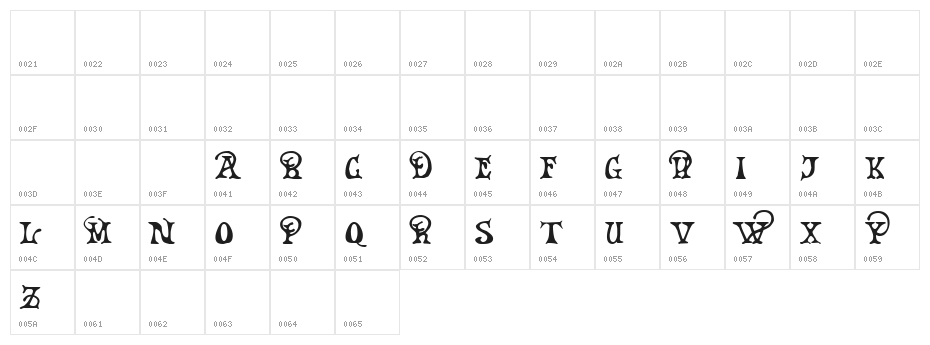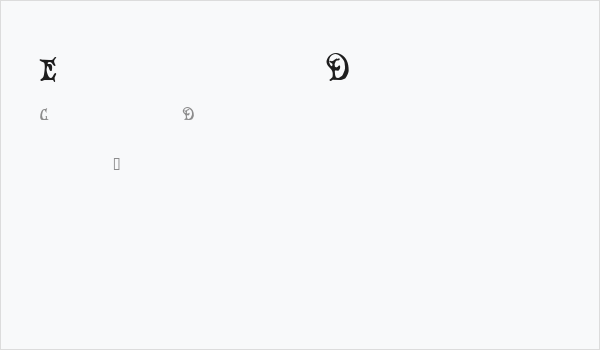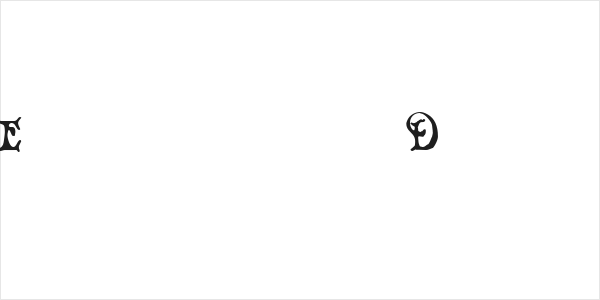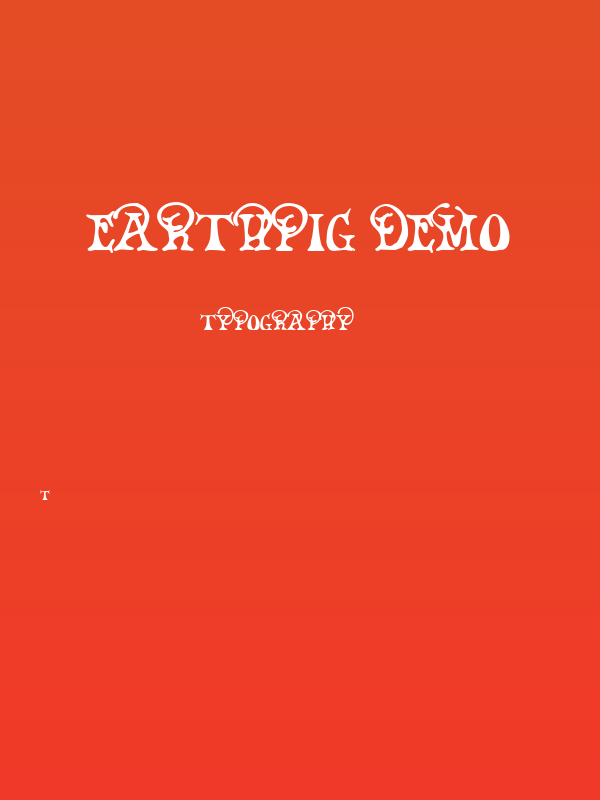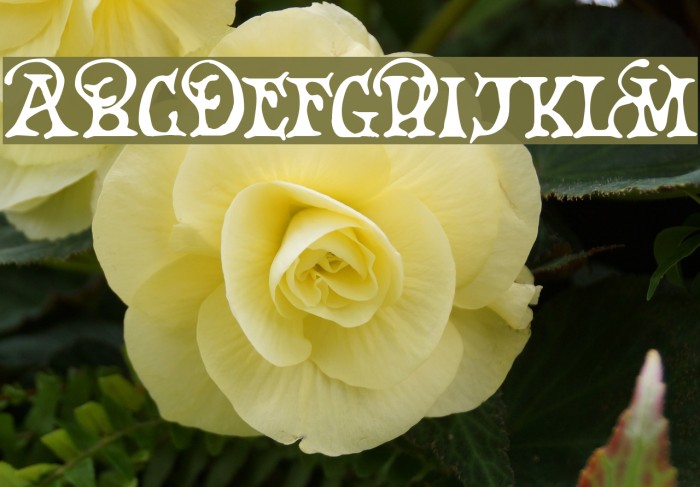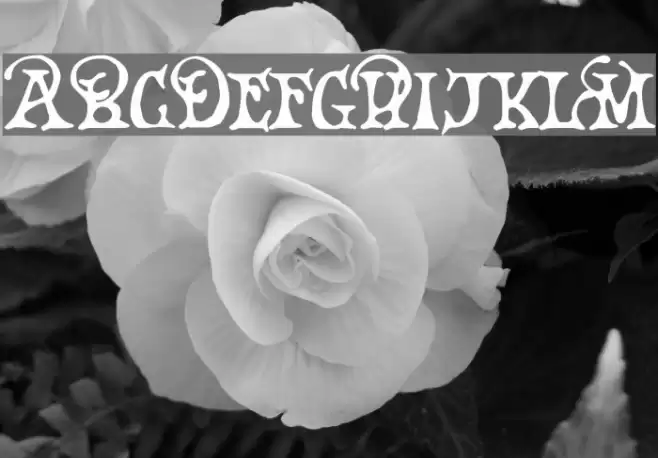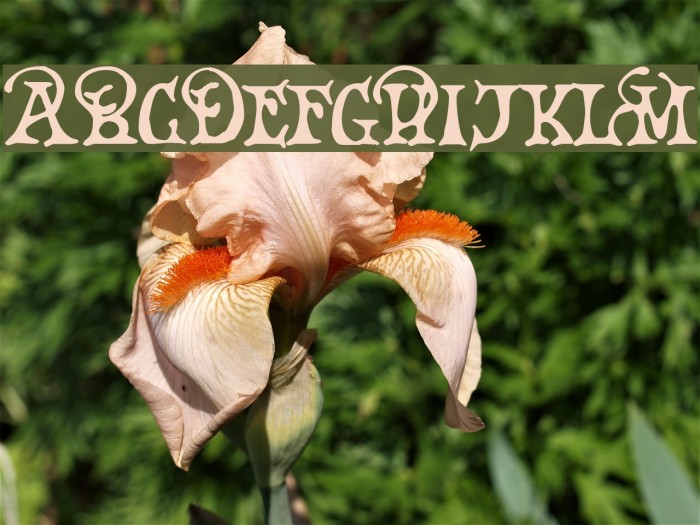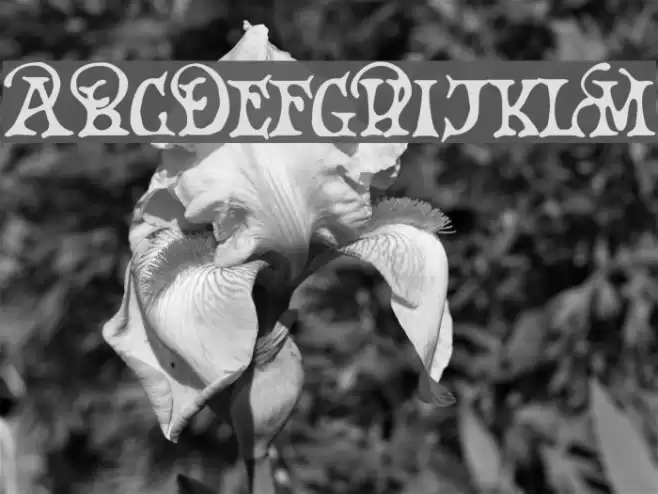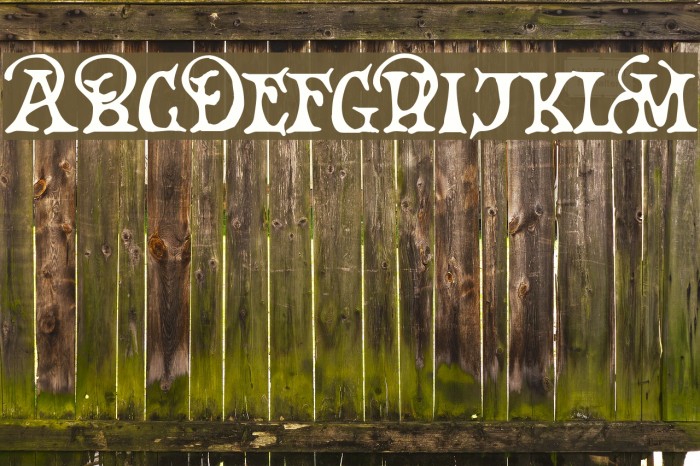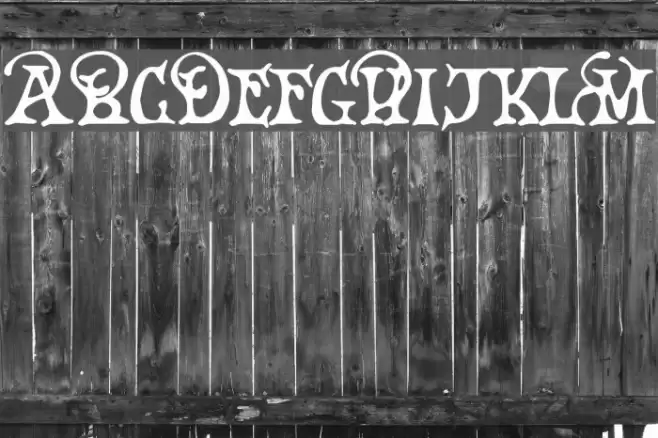
Earthpig Demo Font
| Название | Earthpig Demo |
| Категория | Decorative |
| Область применения | Logos, Headlines, Posters |
| Рекомендуемые проекты | Ideal for fantasy-themed posters, book covers, video game titles, and branding that requires a historical or mystical touch. |